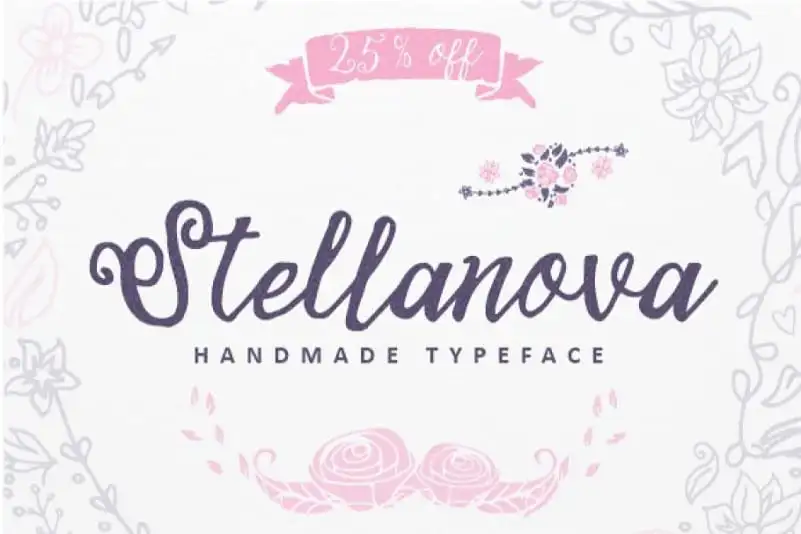
Stellanova Script Font Demo – Download Grátis
Stellanova Script é uma fonte elegante e eterna criada especialmente para aqueles que buscam um toque único em seus projetos digitais. Confortável para uso em qualquer projeto de design, esta fonte está perfeitamente adaptada para criar logos memoráveis ou marcas pessoais. Seu charme autêntico e sua beleza única a tornam um recurso valioso para os designers que buscam dar uma sensação natural às suas criações. Esta fonte é adequada para tudo, desde cartões de convite para casamentos até cartas de boas-vindas, designs retro ou vintage, ou qualquer projeto que precisa de um toque pessoal e autêntico. Os alternativos disponíveis permitem que você personalize ainda mais seus projetos. Hamilton é o designer responsável pela Stellanova Script Font Demo. O uso desta fonte permite aos designers criar trabalhos verdadeiramente únicos e memoráveis, com uma sensação natural e única.